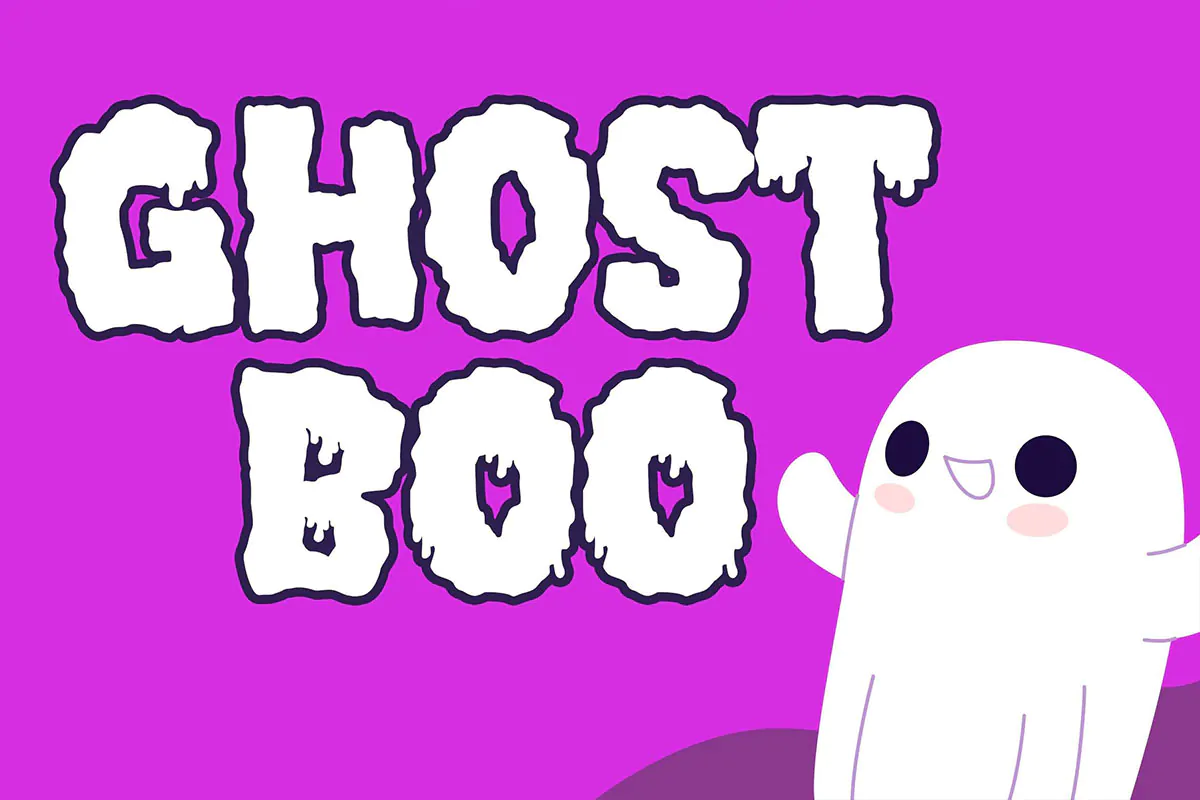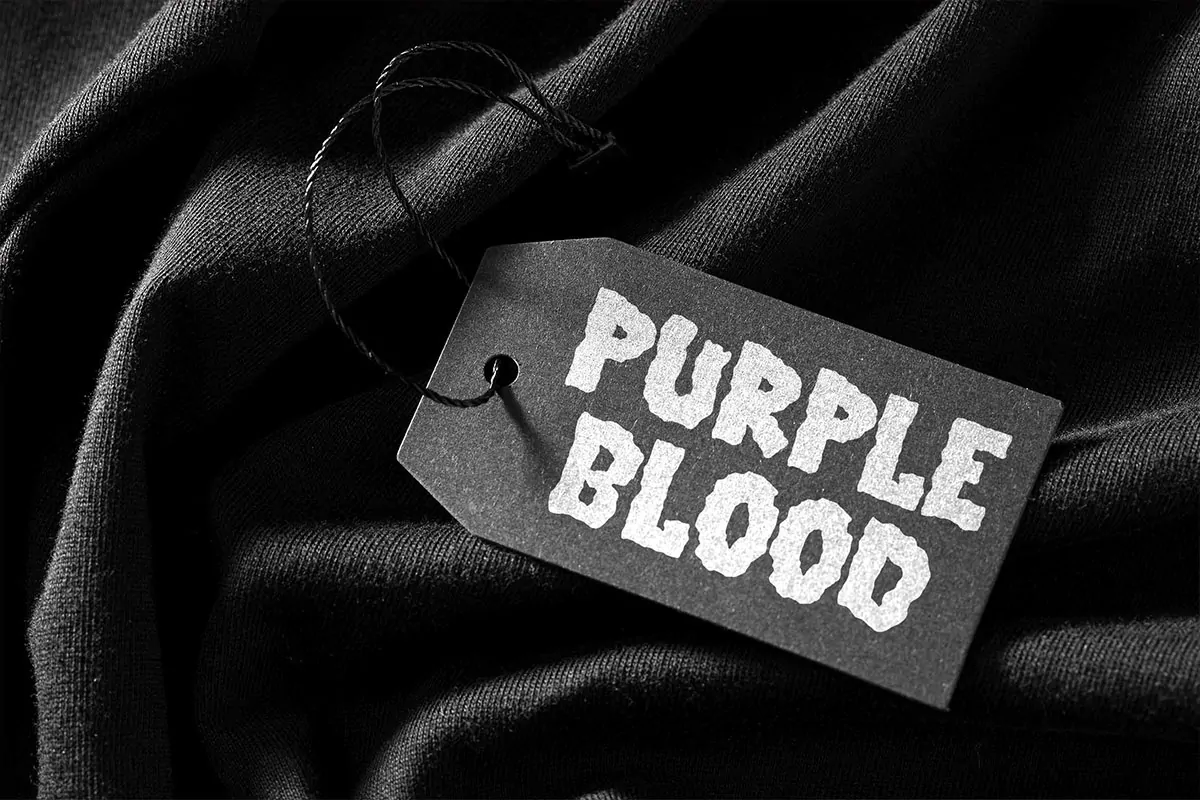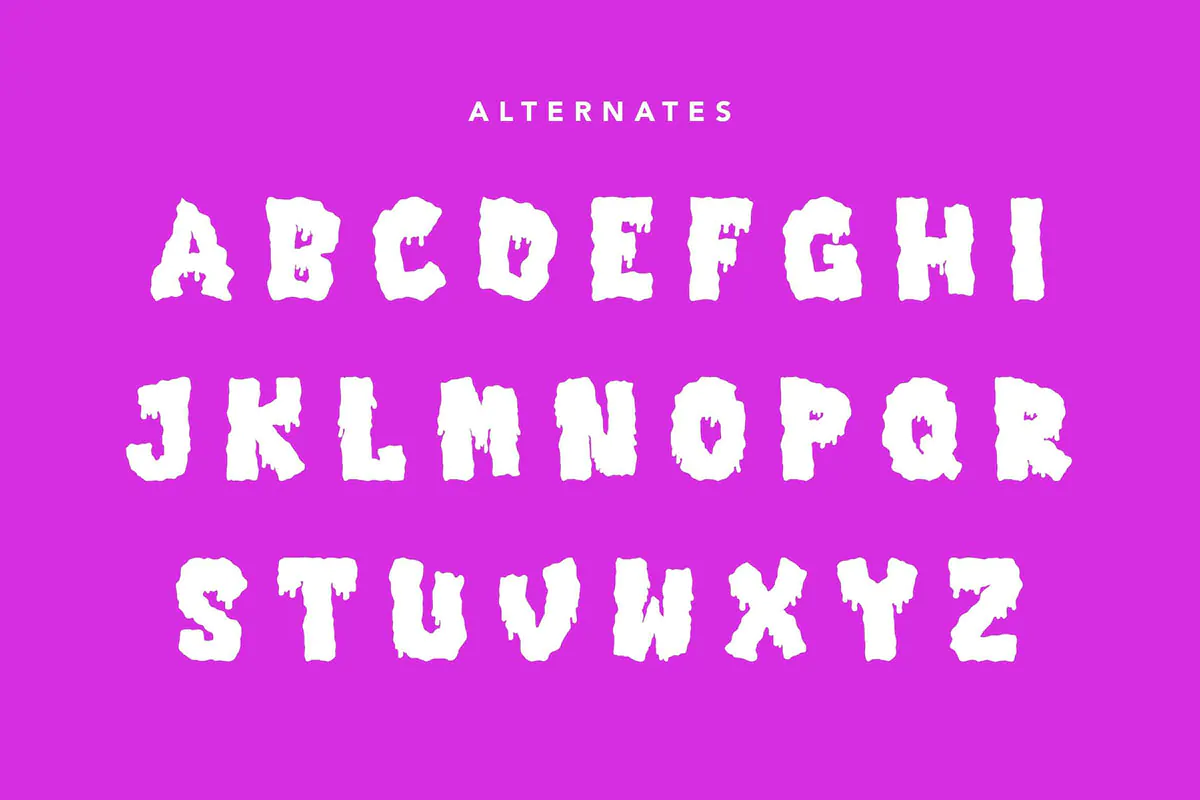
فونت جوهری و کارتونی Toxic
فونت جوهری و کارتونی انگلیسی
فونت جوهری و کارتونی Toxic یک قلم فوق العاده زیبای انگلیسی است که مناسب برای استفاده در طرح و پروژههای گرافیکی مختلف همچون طراحی پوستر، بسته بندی محصولات، انیمیشن، موبایل و وب و … میباشد.